Webフォントの最適化06「size-adjust・ascent-override・descent-override」
Webフォントの最適化01「FOIT・FOUT」にて、Web フォントの課題の一つである FOUT(フォントが入れ替わる際のチラツキ)を紹介しました。
Web フォントの利用の際、切り替わりによってテキストの行数が変化することなどにより、ページのレイアウトが変化してしまいます。これにより、テキストの読み取りの阻害や誤クリックなどのユーザー体験の低下や、CLS(Cumulative Layout Shift、Google が定めるページ読み込み時のレイアウトのズレの大きさの程度を表す指標)スコアの上昇につながってしまいます。
この解決の一助として、CSS の @font-face ルールでは、size-adjust 、ascent-override 、descent-overrideといった設定があります。
これらはフォントの拡大率・アセンダ・ディセンダといった、基本的な寸法を調整するものです。
和文フォントは概ね同じような寸法になっていますので、主に欧文フォントに対して設定することになります。
size-adjust では、フォントの拡大率を調整します。欧文フォントの見かけの大きさは、概ね x-height によって決まります。利用する Web フォントの x-height に合わせて、フォールバックフォントの size-adjust を設定すると、入れ替わった際の見た目のギャップを小さくすることができます。
同様に、フォールバックフォントに対して ascent-override 、descent-override を設定し、利用する Web フォントの、ボディに対するディセンダとアセンダの比率に合わせると良いでしょう。
以下の画像は、左側がAXIS Font ベーシック L 、中央は x-height を参照し Arial を size-adjust で調整して AXIS Font ベーシック L に合わせたもの、右側は Arial をそのまま表示したものです。調整したものは欧文部の見た目の大きさが AXIS Font とある程度揃っているのがわかるかと思います。
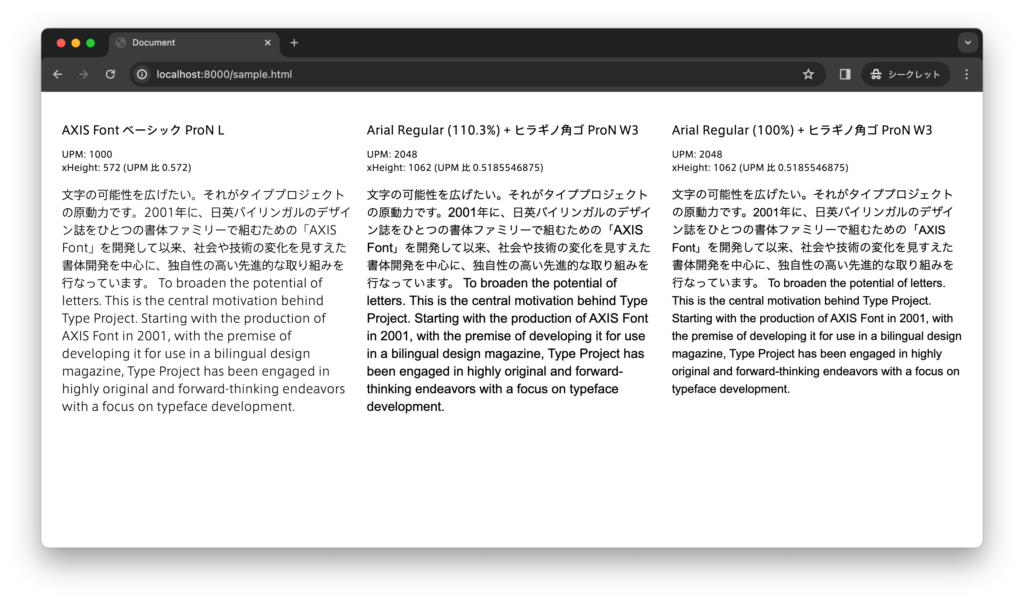
なお、Web フォントの読み込みに何らかの理由で失敗した場合でも、size-adjust 、ascent-override 、descent-override の設定が解除されることはありません。読み込み失敗時でも、可読性を損なわないよう設定しておく必要があります。
ascent-override、descent-override は、2024年1月現在、Safari(macOS, iOS)ではサポートされていないようです。